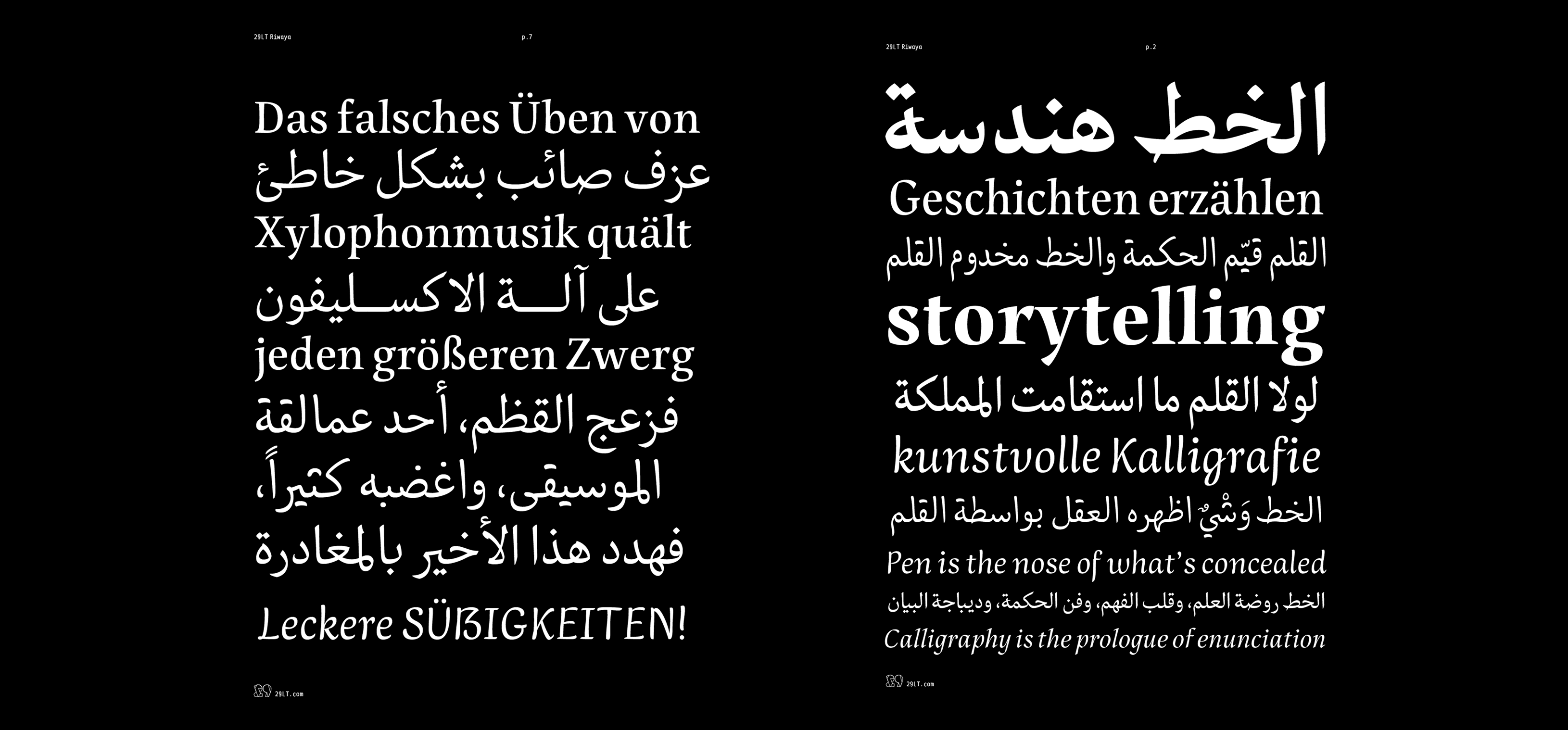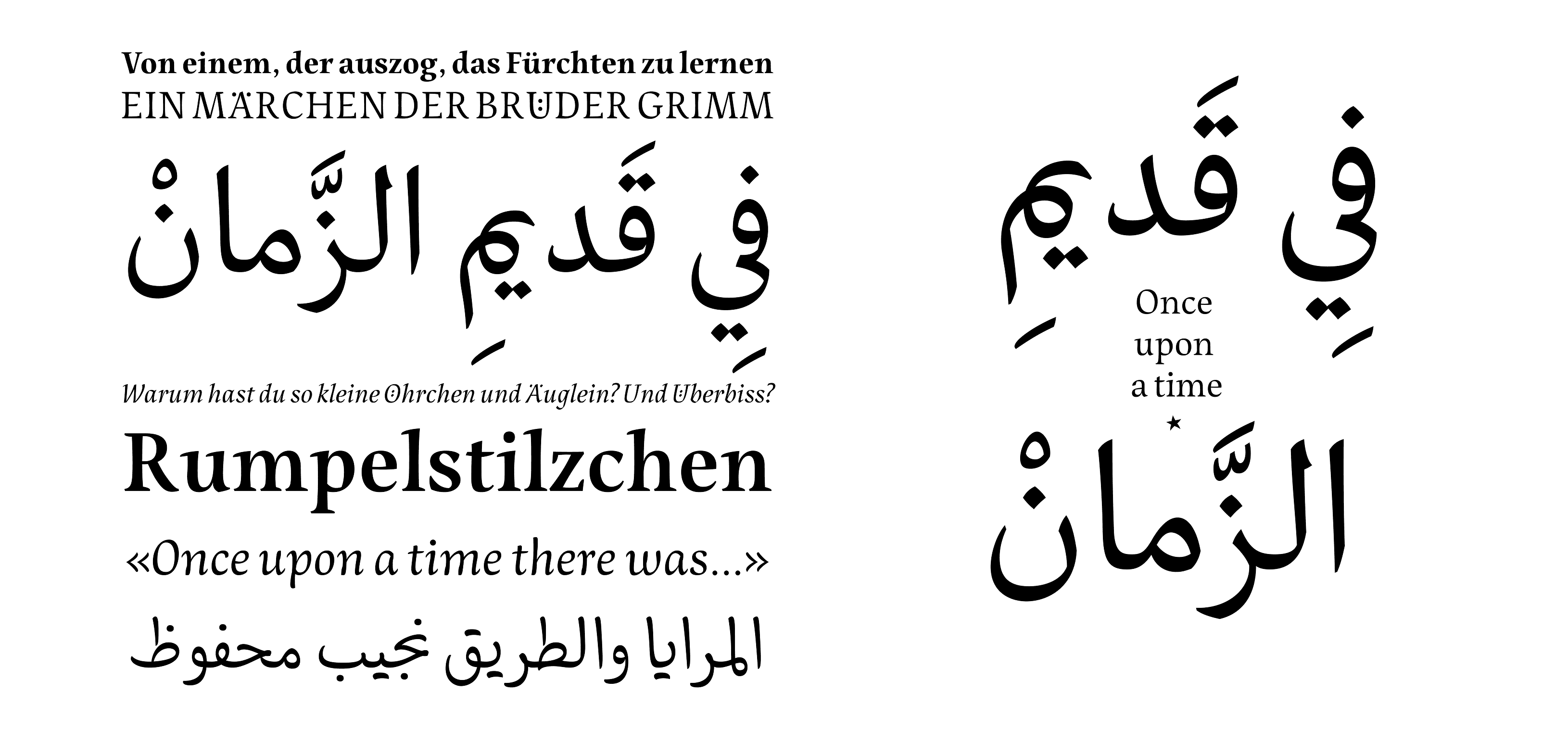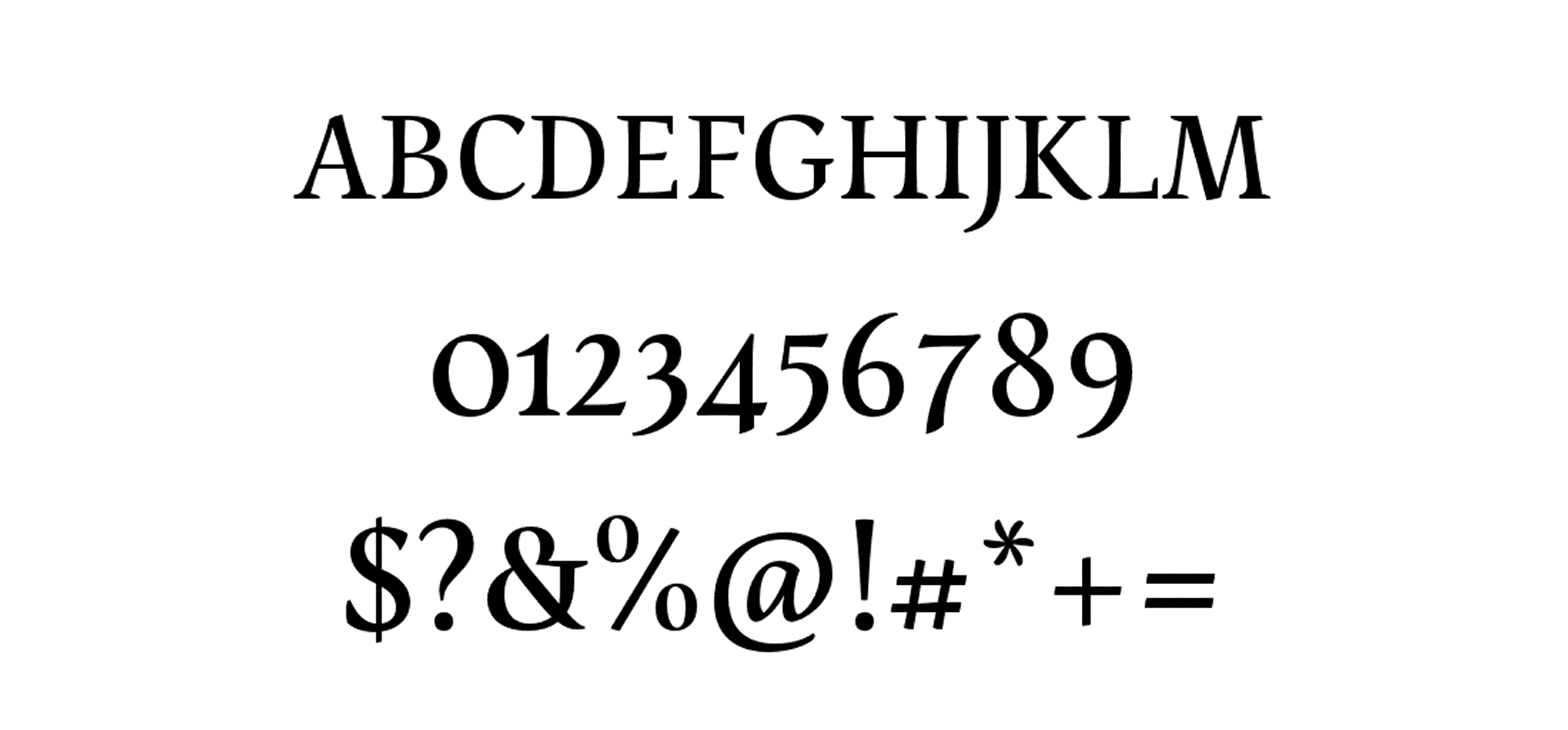
صُمم خط رواية ليمنح النصوص الطويلة طابعًا مريحًا وجذابًا للقراءة، مع وضوح عالي في تفاصيل الحروف يسمح بتتبع المحتوى بسلاسة. يتميّز الخط بأسلوب تقليدي مستلهم من الخط الطباعي الكلاسيكي (Serif)، ويمنح النص صوتًا مميزًا وشخصية متفرّدة.
يُعد مثاليًا للنصوص الأدبية، الروايات، والمحتوى التحريري الذي يعتمد على التسلسل والسرد، حيث يدمج بين الجمالية والبساطة في تجربة القراءة.